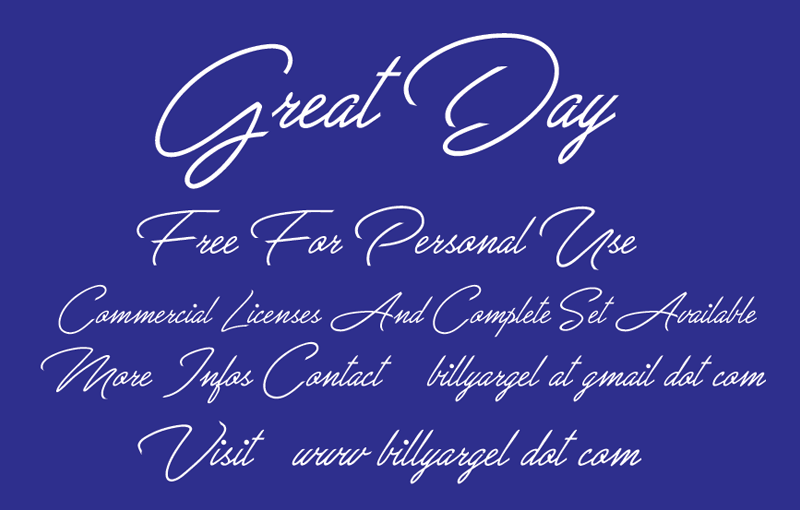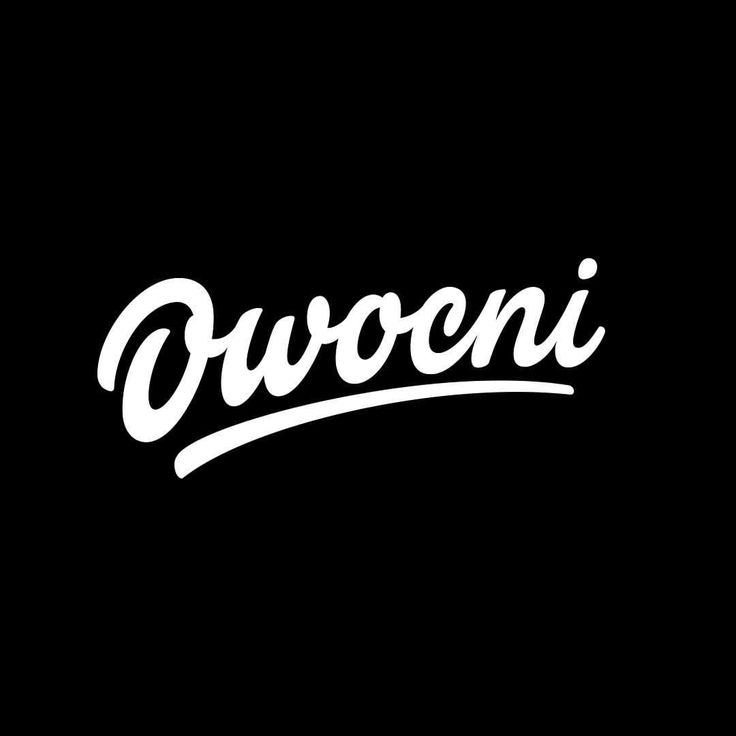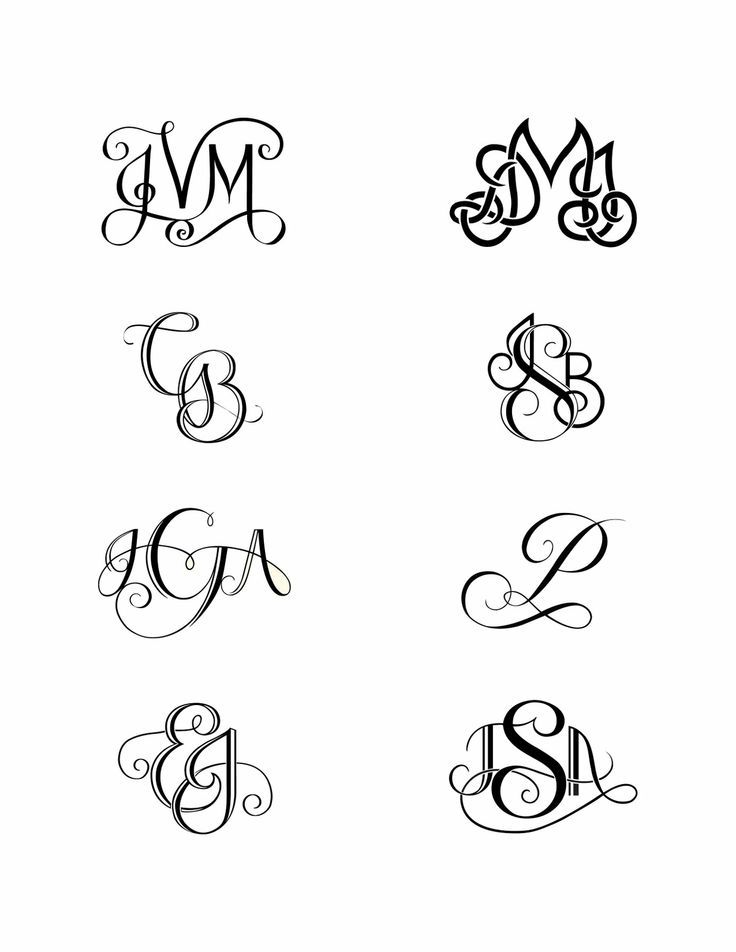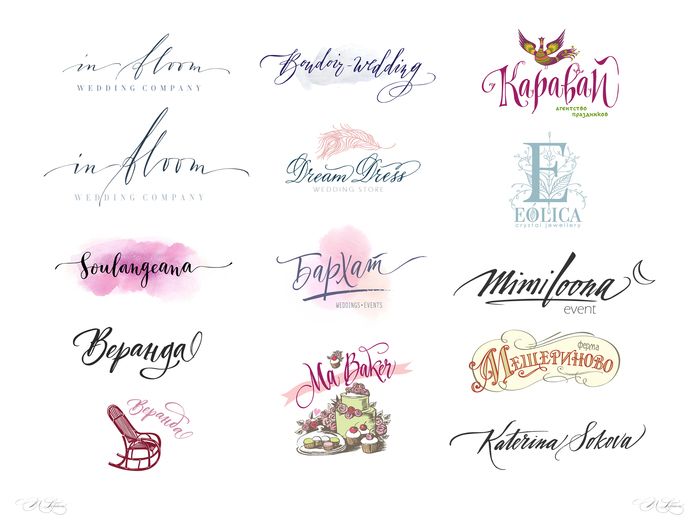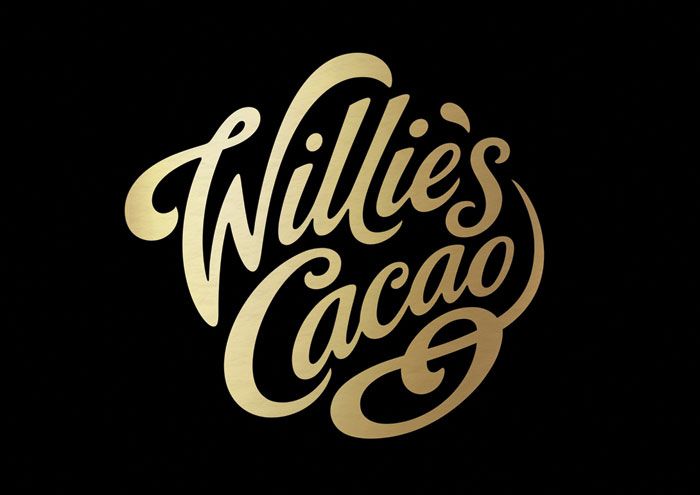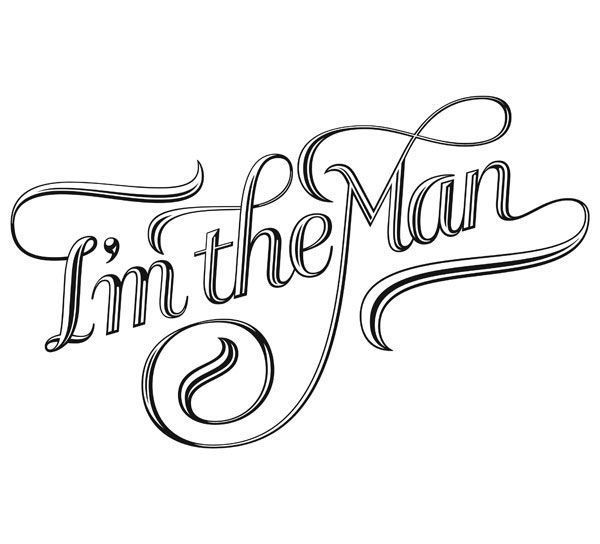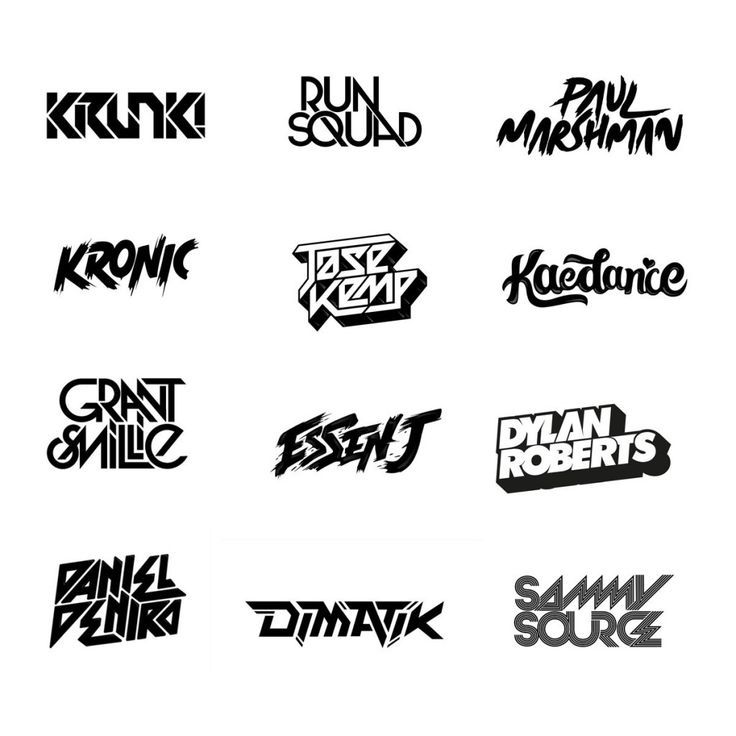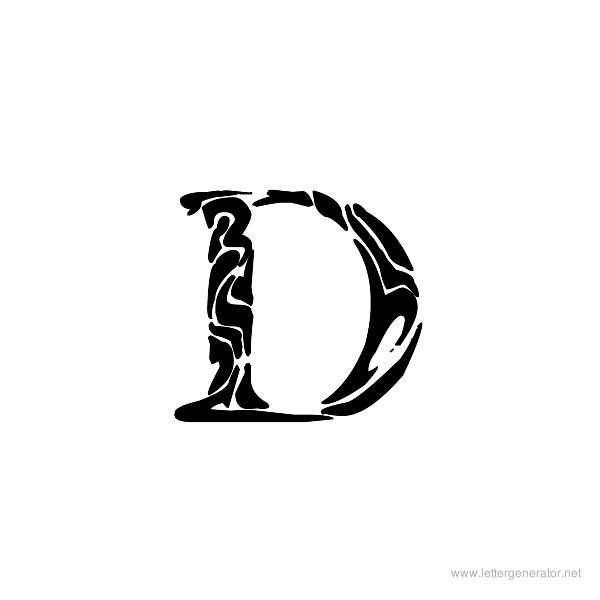
Лучшие шрифты для логотипа, подборка бесплатных кириллических шрифтов для логотипа
Логотип – это лицо компании, которое ассоциирует вас в головах потенциальных клиентов. Поэтому к разработке его дизайна принято подходить максимально серьезно и ответственно, не экономя ни времени, ни сил, ни денег.
Как выбрать лучший шрифт для логотипа
Мы, дизайнеры, постоянно ищем лучшие шрифты для логотипов, поскольку этот элемент является одним из самых функциональных в понятии брендинга. Хороший шрифт всегда легко читается, узнается даже при рассмотрении с далекого расстояния, и эти параметры являются лишь малой частью того, какими качествами должен обладать действительно качественный шрифт.
Давайте рассмотрим еще несколько аспектов, которые помогут бренду выбрать свое стилистическое начертание:
- Учет «лица» компании. Милые и смешные буковки не подойдут для презентации финансового учреждения, как и строгий геометрический шрифт для магазина детских товаров или клиники для малышей.
- Перспектива «долгой жизни». Будет неприятно, если вы заплатите сумму денег дизайнеру, и получите продукт, который будет актуален лишь несколько месяцев, впоследствии теряясь в массе других, более качественных и модных дизайнов. К примеру, шрифт компании Coca-Cola не менялся с самого начала работы компании, и все равно является актуальным, мотивируя все больше творцов для разработки чего-то не менее легендарного и красивого.
- Масштабирование. Буквы и цифры должны выглядеть четко и различимо даже в маленьком размере. Также они не должны терять собственной привлекательности, растягиваясь на большие полотна – помните это.
Это лишний труд и времязатраты, из-за чего дизайнеры все чаще прибегают к шрифтам, распространяющихся по бесплатной лицензии. С одной стороны – это удобно, быстро и универсально. С другой стороны – все это приводит к постоянному копированию, из-за чего легко потеряться в массе других предприятий, которые решили использовать идентичное свободное начертание. Если для небольших компаний и старт-апов этот вариант является оптимальным, то для серьезного бренда это уже не подходит. Представьте, если бы Adidas решили использовать обычный шрифт из программы Word? Уже становится неловко и смешно.
Почему же дизайн шрифта столь важен?
Самые лучшие шрифты для логотипов – это те, что производят приятное впечатление на потенциального клиента, который впервые столкнулся с вашей компанией. Не стоит забывать, что этот эффект может быть негативным, из-за чего к подбору начертания следует подходить с особенной осторожностью и ответственностью. У шрифта есть, скажем, определенный дух, которые может навеять легкие, серьезные, радостные или взбудораживающие эмоции.
Эмоции – самый важный момент, который помогает, либо привлечь, либо оттолкнуть человека, что еще раз говорит о важности грамотного выбора шрифта.
Другим аспектом является то, что люди способны чувствовать, и даже самый маленький диссонанс в написании или стиле общего бренда может заставить клиента усомниться в надобности сотрудничества с вами. Казалось бы, такая мелочь, а каков результат! Многие скажут, что рядовой потребитель может и не разбираться в искусстве. Безусловно, это так. Но некачественный логотип сможет отличить даже тот человек, который никогда в жизни не вникал в тему творчества. Не забывайте – здесь решает не личный творческий профессионализм, а простое чувство, которое появляется в голове и сердце человека, буквально, за несколько секунд.
Шрифт для логотипа с засечками или без?
Лучшие шрифты для логотипов на русском (да и на других языках) делятся на 2 основных категории: с засечками и без них. Особых правил на тему выбора того или иного варианта не существует, поскольку есть такое понятие, как вкус, являющееся решающим в процессе составления плана брендинга.
Но для того, чтобы упростить муки выбора, запомните несколько простеньких советов:
- Засечки на буквах смотрятся более традиционно, из-за чего вызывают определенное ощущение официальности
- Отсутствие засечек навевает чувство современности, поэтому для креативной компании такое начертание может оказаться лучшим решением
Совсем не нужно ограничивать область поиска шрифтами с засечками и без. Посмотрите оригинальные начертания, изготовленные на заказ, но не берите их за основу. Просто вдохновитесь, сравните несколько вариантов, и уже потом выносите собственный вердикт, какие буквы будут «олицетворять» ваш бренд. Дело в том, что излишний креатив может сыграть злую шутку в процессе брендинга, и злоупотреблять этим не стоит. Повторимся еще раз – вкус является основой профессионализма.
Самые красивые бесплатные кириллические шрифты для логотипа
Чтобы вам было немного проще выделить для себя какой-то вариант, в данной статье вы ознакомитесь с красивыми бесплатными шрифтами, которые могут подойти для вас, либо стать основой для разработки уникального дизайнерского начертания.
- Изменяйте одну вещь за раз и оцените, как это отразится на вашем общем дизайне.
- Получить другое мнение. Когда вы работаете слишком близко к чему-то или эмоционально вкладываетесь, вы, как правило, упускаете очевидное.
7. Избегайте неоригинальности
Стремление сделать очевидное сильнее всего, когда вы начинаете работу над дизайном логотипа.
Проработайте его и двигайтесь вперед, чтобы увидеть, как можно использовать разные шрифты так, как другие не могли себе представить. Именно здесь проявляются настоящие творческие способности и дизайнерские навыки.
Например: